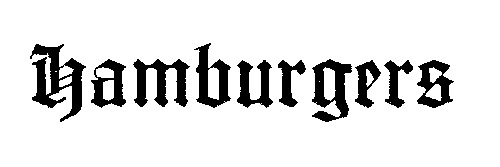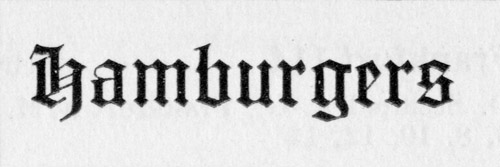
Im Vergleich zum Offset haben die Buchstaben im Buchdruck aber wirklich viel mehr Eigenleben und werden auch stark vom eingesetzten Papier beeinflusst.
Hier einmal Bilder aus dem Seemann, jeweils oben im Bitmap- (Dokumenten-)modus, unten mit Graustufen.
In den guten alten Zeiten, war jede Punktgröße einer Schrift anders geschnitten, und für die spezifische Punktgröße optimiziert.
Bei einer digitalen Font gibt es nur eine Version, die prinzipiell alle Großen setzen kann bzw. muss. Bei der Digitalisierung muss mann eine Große auswählen, als Master für die neue Font zu dienen.
Jedes Mal, dass die Futura digitalisiert war, war eine andere Master wahrscheinlich verwendet. Deswegen sehen die Buchastaben in den verschiendene Versionen heute alle anders aus. Ebenso mit den Laufweiten.
Wenn ich die Neufville nehme und merke, daß sie von der Laufweite her anders läuft als die Bleisatz-Futura - dann müßte ich die Laufweite doch generell korrigieren können, richtig?
Was mich irrigiert ist Georg's Bemerkung, daß er keine ch Ligatur bei der Neufville-Futura gefunden hat. Wie soll ich denn sonst Preußi ch es setzen?
Ich nehme die Neufville. Dann kann ich den Schriftzug daraus für die Webseite gestalten und meine Bleisatz-Buchfuture für die Briefbogen und Visitenkarten verwenden.
Ein ch Ligatur ist für eine moderne geometrische Schrift nicht notwendig, selbst wenn es schon mal im Blei gegossen war. Nicht alles, was früher passierte, war richtig, gut, oder klug ;-)
Die Neufville Futura ist eine herrvoragende Digitalization und eine herrvoragende Schrift, selbst wenn sie nicht eins-zu-eins mit der Bleisatz-Version vergleichbar ist.
Es geht mir nur und ausschließlich um Authenzität.
Ich denke nie rückwärtsgerichtet. Konservativ bedeutet, das Gute und Sinnvolle zu Bewahren. Aber durch neues Gutes und Sinnvolles zu ergänzen.
Was bedeutet "eine moderne geometrische Schrift" braucht das nicht?
Heißt das, daß das "c" rechts und das "h" links sowieso eine geringere Dickte haben? So daß eine Ligatur praktisch automatisch entsteht bei einer ch-Kombination?
Die Neufville Futura ist eine herrvoragende Digitalization und eine herrvoragende Schrift, selbst wenn sie nicht eins-zu-eins mit der Bleisatz-Version vergleichbar ist.
Es muß halt stimmig passen, weil ich im Buchdruck mit meiner Bleisatz-Buchfutura z.B. meine Briefbogen und Visitenkarten drucken werde.
Was hältst Du grundsätzlich von meiner Entscheidung, den Schriftzug künftig über die Buchfutura zu bauen statt der Fraktur?
nein. für deinen eindruck den du schaffen willst ist die ch-ligatur sicher ok. nur heute braucht man sie nicht, da sie ja früher den 2. griff in den setzkasten ersparen sollte. die lesbarkeit wird durch diese ligatur ja kaum verbessert.
Mir geht es halt so:
Egal, was und warum ich etwas lese, ich lese automatisch Korrektur.
Eine nicht vorhandene Ligatur fällt mir sofort auf. Mein Blick stockt.
Nenn's Ligatur-Fixierung.
Ich möchte mein Preußi Lang-s ch-Ligatur es Blei Lang-s atz-Magazin
unbedingt mit ch-Ligatur und mit Lang-s.
Wenn du Authentisch sein willst, musst du alles mit Bleisatz drucken. Leider ist es so. Du kannst nicht das Bleisatz-Druck mit digitalen Werkzeug reproduzieren. Sie sind komplett andere Medien, und sie funktionieren total anders.
Genau! Bei Frakturschriften sind die c's beim ch manchmal Anders als beim "normalen" c (obwohl das c im deutschen fast immer mit h oder k vervolgt wird), und/oder es gibt eine Verbindungsstrich zwischen den Buchstaben-Formen. Das kommt aus das Schreiben. Bei der Futura passiert dies nicht. Du hast ein c, und ein h. Mit Bleisatz war es vielleicht Zeitsparend, diese zwei Buchstaben als Ligatur einzusetzten. Aber da es kein ch Taste auf dem Tastatur gibt, ist dies jetzt eine andere Situation.
Es wird auch stimmig passen. Selbst wenn die Bleisatz- und Digiatlversionen anders sind.
Ich habe eine ganze Reihe von Futura-Schnitten mit Lang-s.
Mal sehen, wie es aussieht, wenn es fertig ist.
Im Moment sähe ich die Lang-s als eine Art Hingucker, als Catch Eye.
Was ich bei deiner Schriftzug komisch finde, ist nicht die Schrift, sondern das Wort "preußisch" ;-)